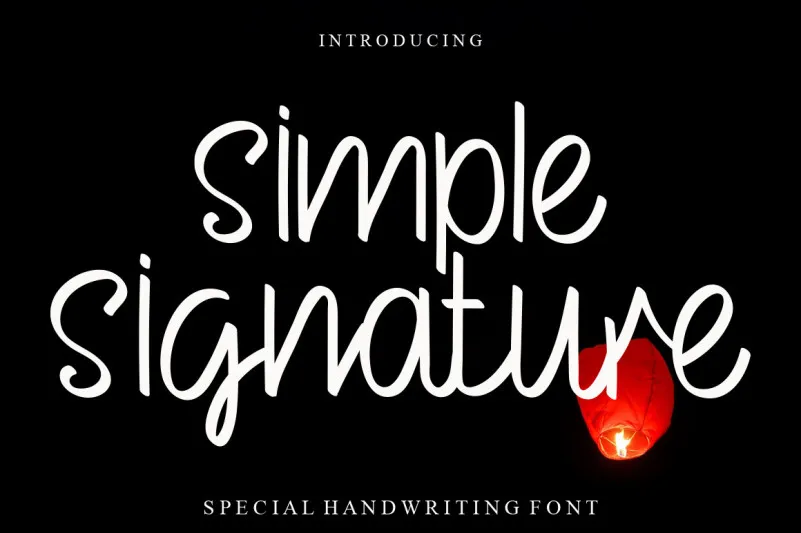
Simple Font – Download Grátis
A Simple Font oferece uma opção elegante para quem busca um estilo artesanal em suas criações digitais. Se você procura por um script elegante e fluido, este é seu fonte perfeito. Confortável de ler e muito versátil, essa fonte leva um toque de criatividade a qualquer projeto que você trabalha. Ideal tanto para uso pessoal quanto profissional, a Simple Font se destaca pela sua simplicidade e facilidade de utilização, tornando-a uma escolha ótima para designers, amantes do design ou até mesmo aqueles que buscam um estilo retrô em suas criações digitais. Com sua beleza clara e fluida, ela transformará seus trabalhos digitais num toque especial, como se eles fossem de outro mundo. Além disso, o designer levincreative criou uma fonte cuidadosamente pensada que é perfeitamente adaptável a muitas necessidades de projeto. Seja para criar um e-mail personalizado com um toque autêntico ou desenvolver novos materiais publicitários, a Simple Font será sua escolha ideal. Incorporando esse novo estilo de letra na sua próxima criação é algo que você definitivamente não vai querer perder. Experimente o seu único e singular toque de beleza neste fantástico script!